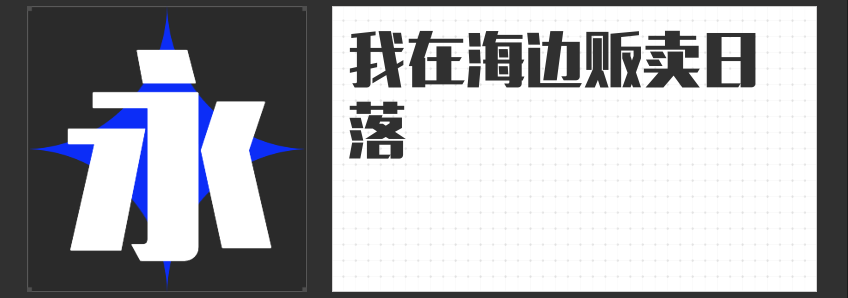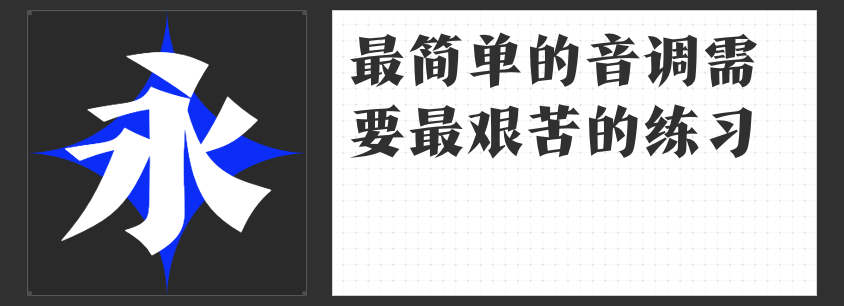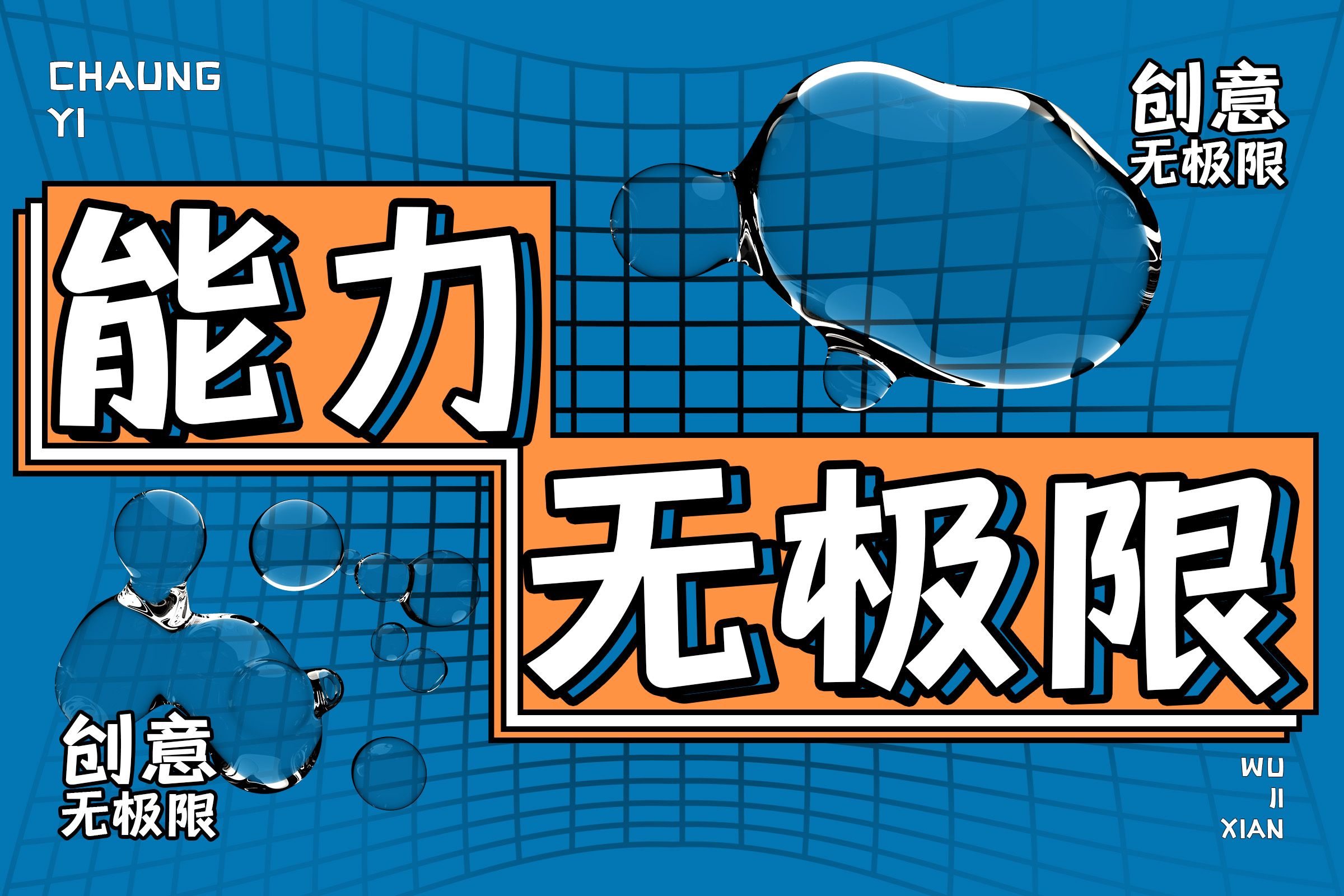
为开学季和社团招新增添创意——四款精选字体介绍
随着新学期的到来,校园里又将迎来一波热闹非凡的社团招新活动。为了吸引新生们的注意,制作一份创意十足的宣传材料显得尤为重要。今天,我们就为大家推荐四款适合用于开学及社团招新宣传设计的字体,帮助你的海报、视频等设计作品更加出彩!
1.高手字斋东京体
作为一款庄重而严肃的字体,“高手字斋东京体”非常适合用于制作宣传视频。其独特的笔触和布局设计,能够让视频中的文字部分显得格外引人注目。无论是用来介绍学校的悠久历史,还是展示社团的风采,“高手字斋东京体”都能为你的视频增添一份沉稳而不失格调的气息。这种字体特别适合正式场合的开场白或者重点内容的强调,让观众留下深刻印象。
2.励字志向黑简 大粗
对于开学宣传以及社团招新的海报设计而言,“励字志向黑简 大粗”是一个稳重大气的选择。这款字体采用了大粗的笔画,能够很好地突出海报的主题,给人一种积极向上的感觉。无论是学院的官方海报,还是学生组织的自我介绍,“励字志向黑简 大粗”都能够传递出一种自信和热情,激发新生们对未来的憧憬。
3.励字造灿烂黑
当谈到开学迎新和文化类社团招新的海报设计时,“励字造灿烂黑”无疑是一个理想的选择。这款字体以其流畅而富有活力的线条,营造出一种欢快、明亮的氛围。它不仅适合用于展现校园生活的多彩面貌,还能够很好地体现文化类社团的独特魅力。如果你想要制作一张既美观又充满生机的海报,“励字造灿烂黑”将是你不错的选择。
4.喵字文创体
最后,对于那些二次元爱好者和追求可爱风格的社团而言,“喵字文创体”绝对是一款不可多得的字体。它以其圆润可爱的字形和俏皮的风格,在众多字体中脱颖而出。无论是动漫社、Cosplay社还是其他创意社团的招新海报,“喵字文创体”都能够吸引到目标群体的目光,让他们感受到社团的热情和友好。
综上所述,这四款字体各具特色,可以满足不同场合和不同风格的宣传需求。它们不仅能提升宣传材料的视觉效果,还能更好地传达出你所要表达的信息。希望今天的推荐能为你的开学季和社团招新宣传活动带来更多灵感和创意!